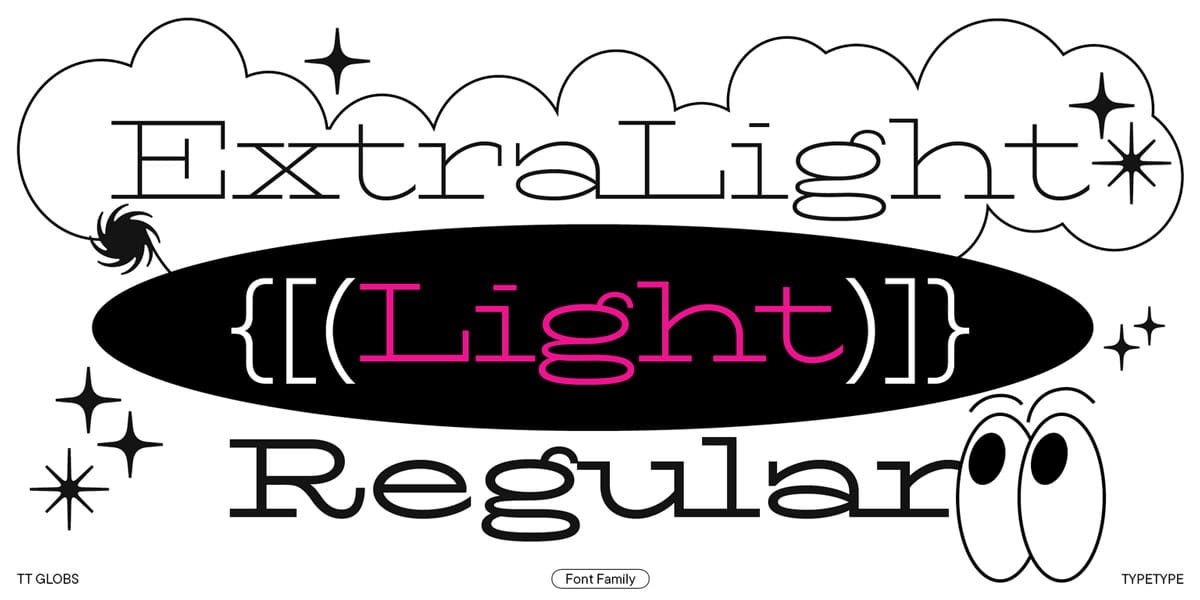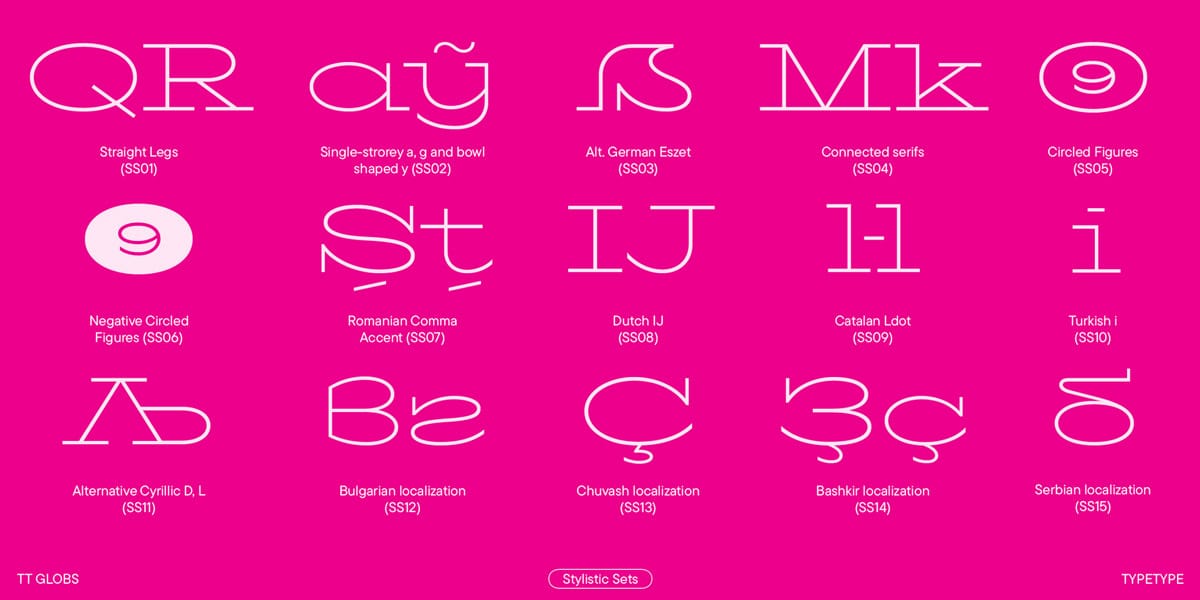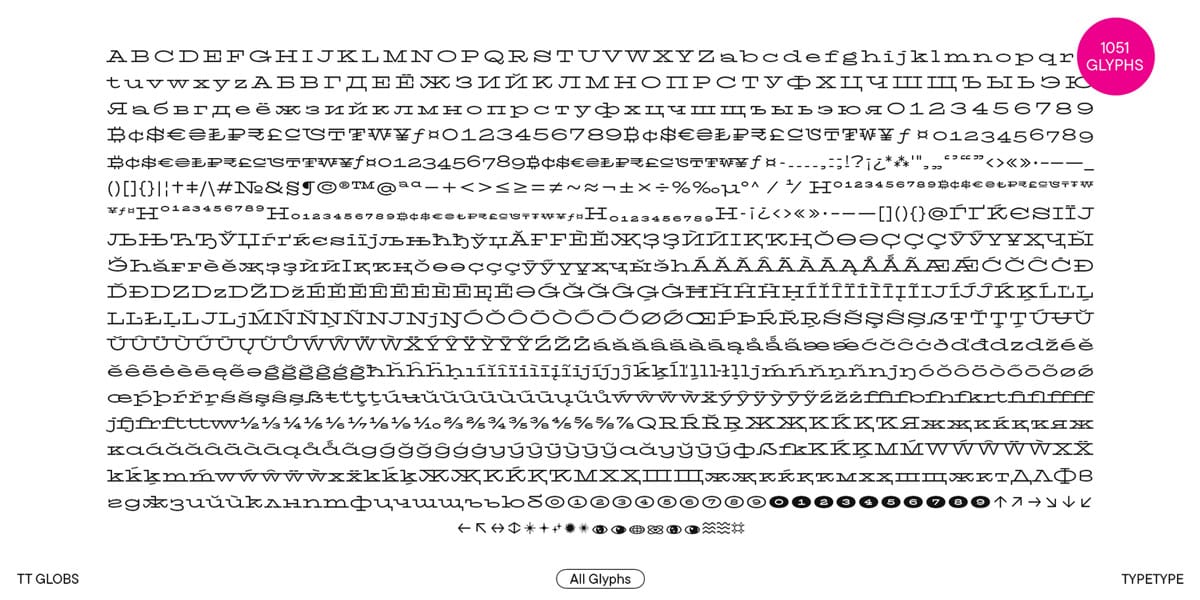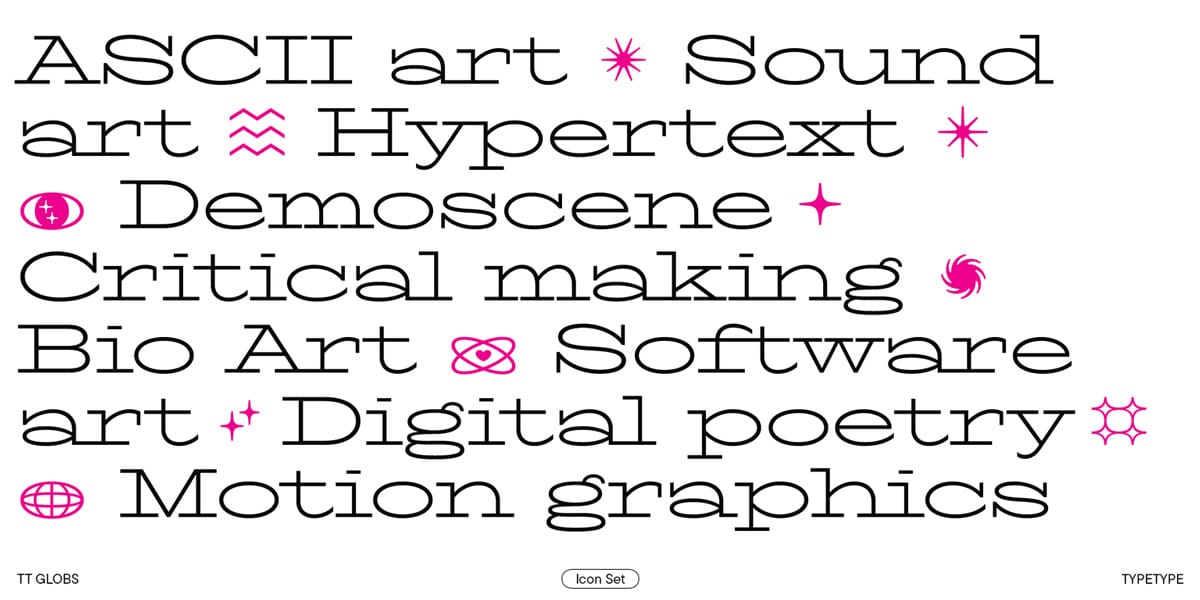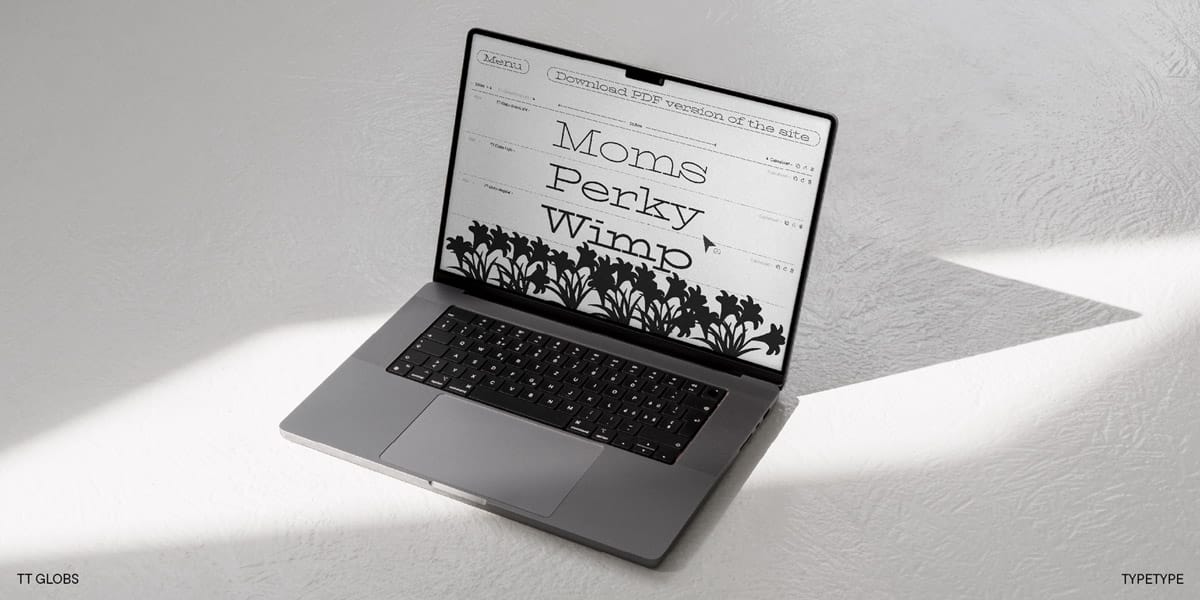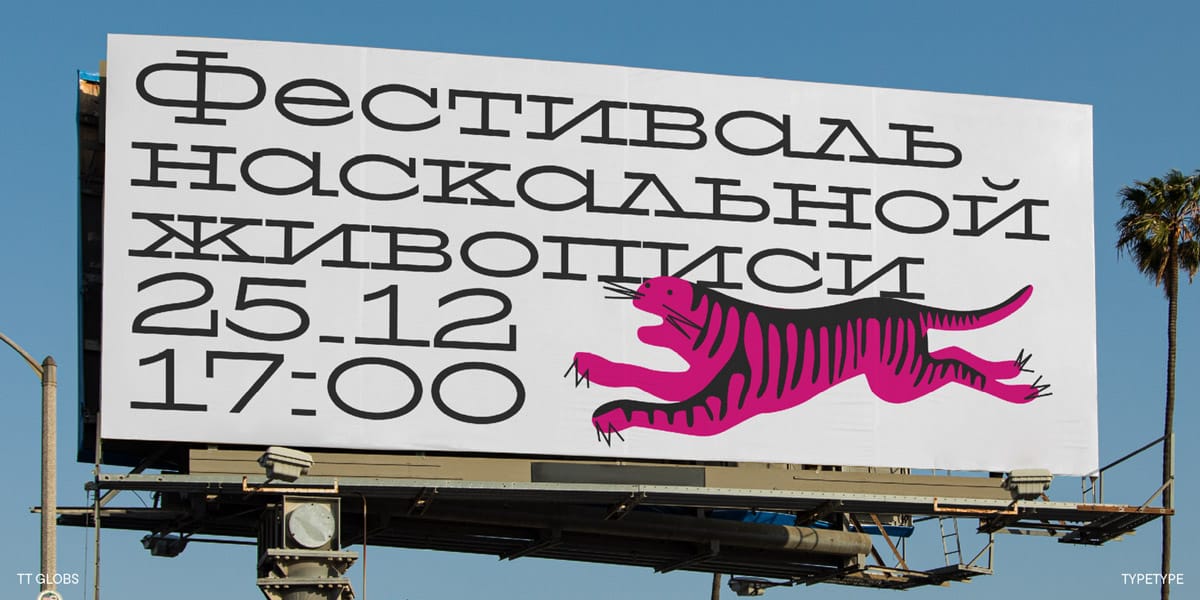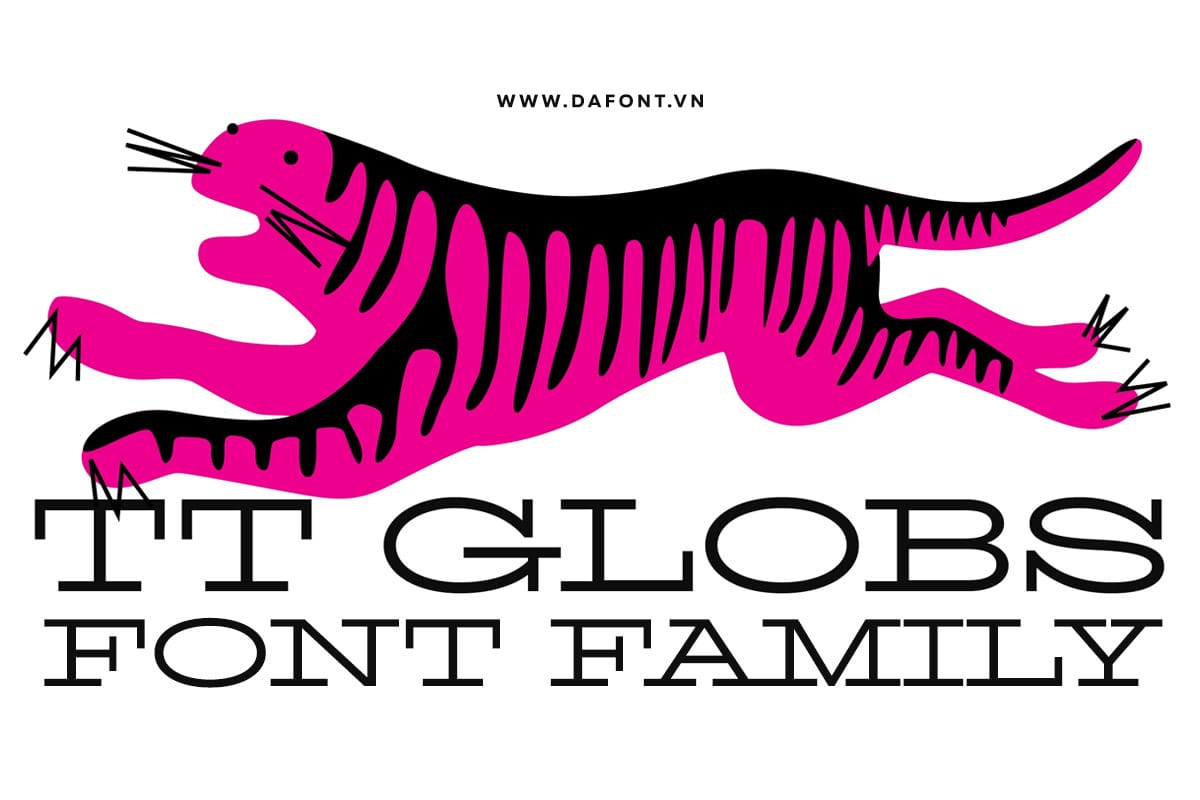
TT Globs là một trong những font slab serif đẹp, hiện đại và cực kỳ nổi bật trong bộ sưu tập fonts của TypeType Foundry. Với phong cách cá tính, tỉ lệ chữ được kéo dài cùng chân serifs ấn tượng, TT Globs đem đến một diện mạo mạnh mẽ nhưng vẫn đầy tính nghệ thuật cho mọi thiết kế.
Font được thiết kế để kết hợp giữa cổ điển và hiện đại, cho phép người dùng dễ dàng áp dụng trong branding, thiết kế logo, poster hay các ấn phẩm quảng cáo đòi hỏi cá tính rõ nét.
Những đặc điểm nổi bật của TT Globs
Không giống như những font Slab Serif cứng nhắc, TT Globs sở hữu những nét vẽ rất “phiêu”:
- Serif kéo dài và tỷ lệ chữ rộng: Các chân chữ được kéo dài tạo nên một nhịp điệu thị giác liên tục, giúp các tiêu đề (headlines) trở nên nổi bật và có tính gắn kết cao.
- Đường nét bất đối xứng: Các chi tiết ở chân chữ (K, R, Я) hay đuôi chữ (g, y) được thiết kế dạng sóng hoặc uốn lượn mềm mại, xóa tan cảm giác khô khan.
- Tính linh hoạt cao (Variable Font): Với phiên bản Variable, nhà thiết kế có thể tùy chỉnh độ đậm nhạt (Weight) và các thông số khác một cách mượt mà để phù hợp với từng không gian thiết kế.
Tính năng OpenType
Bộ font này được TypeType đầu tư kỹ lưỡng về mặt kỹ thuật:
- 4 Style đa dạng: Từ ExtraLight thanh mảnh đến Regular vững chãi + thêm 1 variable, đáp ứng mọi nhu cầu từ web đến in ấn.
- Hơn 1000 ký tự: Bao gồm đầy đủ bộ chữ cái, số, ký hiệu tiền tệ và các ký tự đặc biệt.
- 33 Tính năng OpenType: Cho phép bạn thay đổi các kiểu chữ cái thay thế (Stylistic Sets) để tạo ra diện mạo mới lạ cho logo hay typo.
- Hỗ trợ đa ngôn ngữ: Hỗ trợ hơn 230 ngôn ngữ khác nhau, giúp các dự án quốc tế trở nên dễ dàng hơn bao giờ hết.
Ứng dụng của TT Globs trong thiết kế
Nhờ phong cách độc đáo, TT Globs đặc biệt phù hợp cho:
- Branding & Identity: Phù hợp cho các thương hiệu thời trang, trang sức, quán bar trendy hoặc các lễ hội âm nhạc.
- Poster & Headline: Với kích thước lớn, font chữ này tạo ra tác động thị giác cực mạnh.
- Thiết kế bao bì: Tạo cảm giác thủ công (craft) nhưng vẫn rất hiện đại và cao cấp.
- Street Art & Exhibition: Thể hiện sự tự do và phá cách trong nghệ thuật đường phố.